Font chữ kiến trúc Việt hóa là nhóm các phông chữ mô phỏng lại nét chữ viết tay kỹ thuật trên các bản vẽ Blueprint hoặc phong cách thiết kế hình học tối giản của ngành xây dựng. Với đặc trưng là các nét vẽ dứt khoát, sạch sẽ và mang đậm tính phác thảo, bộ font này là lựa chọn tuyệt vời cho các dự án nhận diện thương hiệu nội thất, bao bì phụ kiện kỹ thuật hay poster dự án kiến trúc. Doozypack.vn chia sẻ link tải bộ font kiến trúc Việt hóa chuẩn, hỗ trợ đầy đủ bảng mã Unicode để bạn sáng tạo những ấn phẩm mang phong cách kỹ nghệ độc đáo.
Đặc điểm thẩm mỹ của bộ font chữ kiến trúc đẹp
Một bộ phông chữ kiến trúc chất lượng không chỉ mang tính trình bày mà còn phải truyền tải được cái “gu” thẩm mỹ và sự tỉ mỉ của người làm nghề thiết kế.
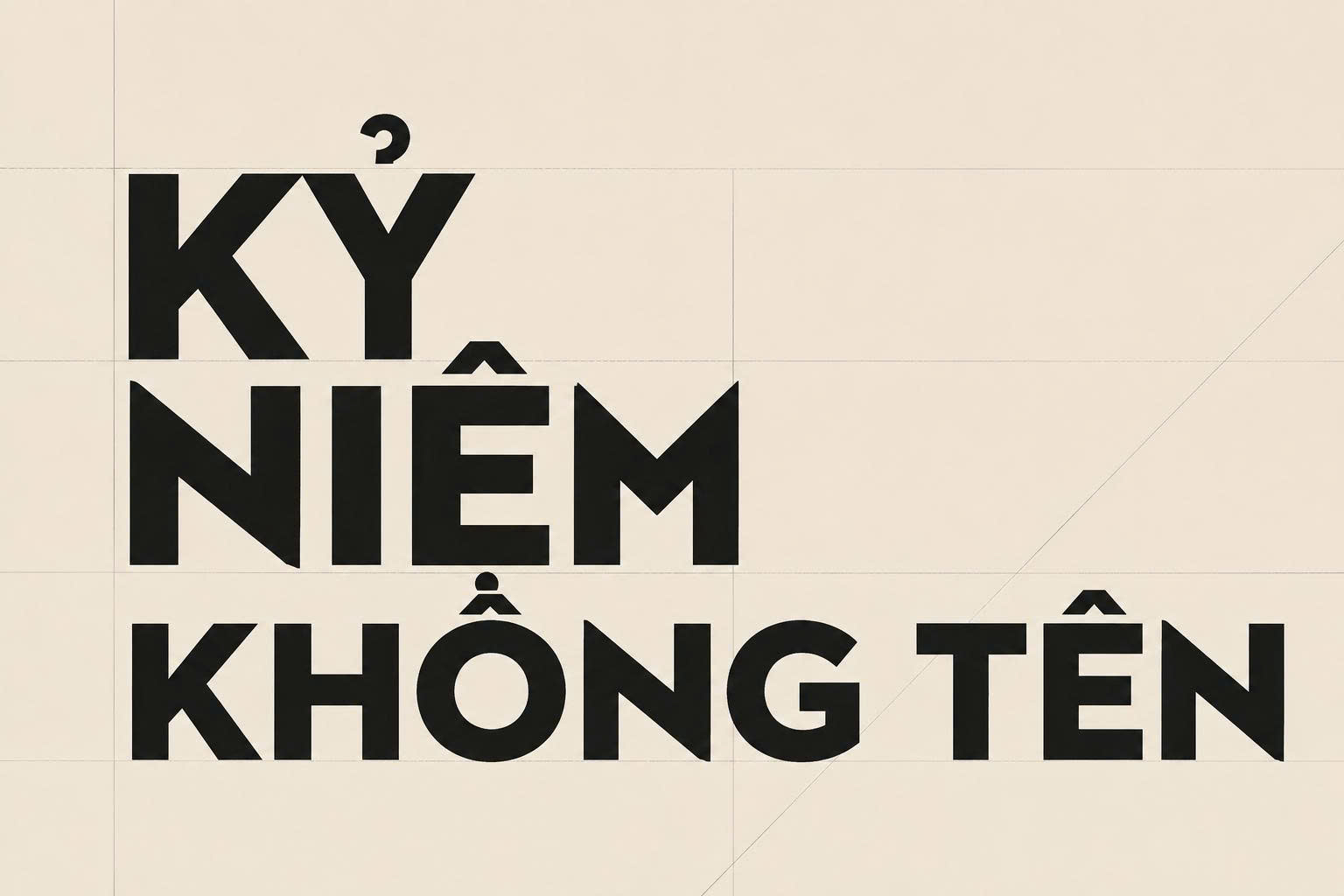
Nét vẽ tay kỹ thuật (Handwriting Drafting)
Đặc trưng lớn nhất của font chữ kiến trúc đẹp dòng viết tay là các đường nét mô phỏng áp lực của bút kim trên giấy can. Các ký tự thường có chiều cao đồng nhất, nét chữ mảnh nhưng rõ ràng, tạo cảm giác mộc mạc nhưng vô cùng chuyên nghiệp. Phong cách này gợi nhắc đến sự tận tâm của kiến trúc sư trong từng bản phác thảo sơ phác ban đầu.
Cấu trúc hình học tối giản và chuẩn xác
Ngoài dòng viết tay, font kiến trúc còn bao gồm các phông chữ không chân (Sans-serif) được xây dựng trên các khung hình học cơ bản. Những bộ font này nhấn mạnh vào sự minh bạch, hiện đại và tính logic cao. Khi được Việt hóa tại Doozypack.vn, hệ thống dấu thanh được tinh chỉnh để không làm phá vỡ sự cân bằng của các nét vẽ kỹ thuật, đảm bảo văn bản luôn thông thoáng.
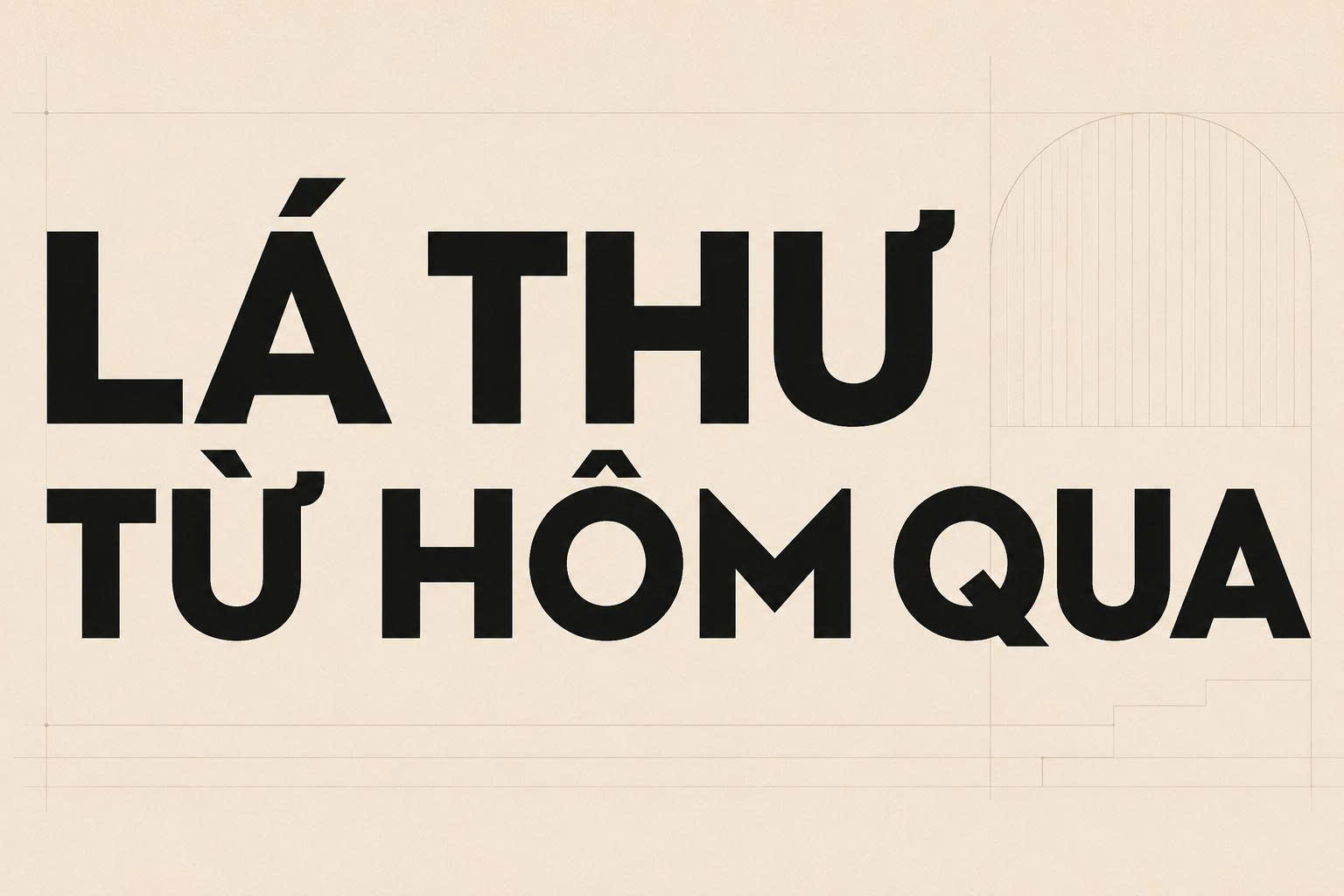
| Nhóm Font | Đặc điểm thị giác | Ứng dụng đề xuất tại Doozypack.vn |
| Font Phác thảo (Drafting) | Viết tay, mộc mạc | Dùng cho tem nhãn sản phẩm thủ công, thiệp mời studio kiến trúc. |
| Font Kỹ thuật (Technical) | Sạch sẽ, chuẩn xác | Dùng in thông số kỹ thuật, hướng dẫn lắp đặt trên vỏ hộp. |
| Font Hình học (Geometric) | Hiện đại, tối giản | Thiết kế Logo, tiêu đề trên túi giấy doanh nghiệp xây dựng. |
Tại sao designer nên tải font kiến trúc Việt hóa cho bao bì?
Trong ngành thiết kế và sản xuất bao bì tại Doozypack.vn, nhóm font chữ này mang lại những giá trị thực tế vượt trội:
- Giải quyết triệt để lỗi font: Việc sử dụng bản Việt hóa chuẩn giúp bạn gõ các từ khóa chuyên ngành như “Thiết kế bền vững”, “Vật liệu tự nhiên” một cách trọn vẹn, không bị lỗi nhảy dấu ở các chữ có dấu đặc thù như ơ, ư, đ.
- Khẳng định uy tín thương hiệu: Font chữ phong cách kiến trúc tạo cảm giác về một doanh nghiệp có chuyên môn cao, làm việc khoa học và bài bản.
- Tính ứng dụng linh hoạt: Phù hợp cho cả việc làm tiêu đề chính trên hộp quà tặng lẫn trình bày các thông số kỹ thuật chi tiết trên nhãn dán sản phẩm.
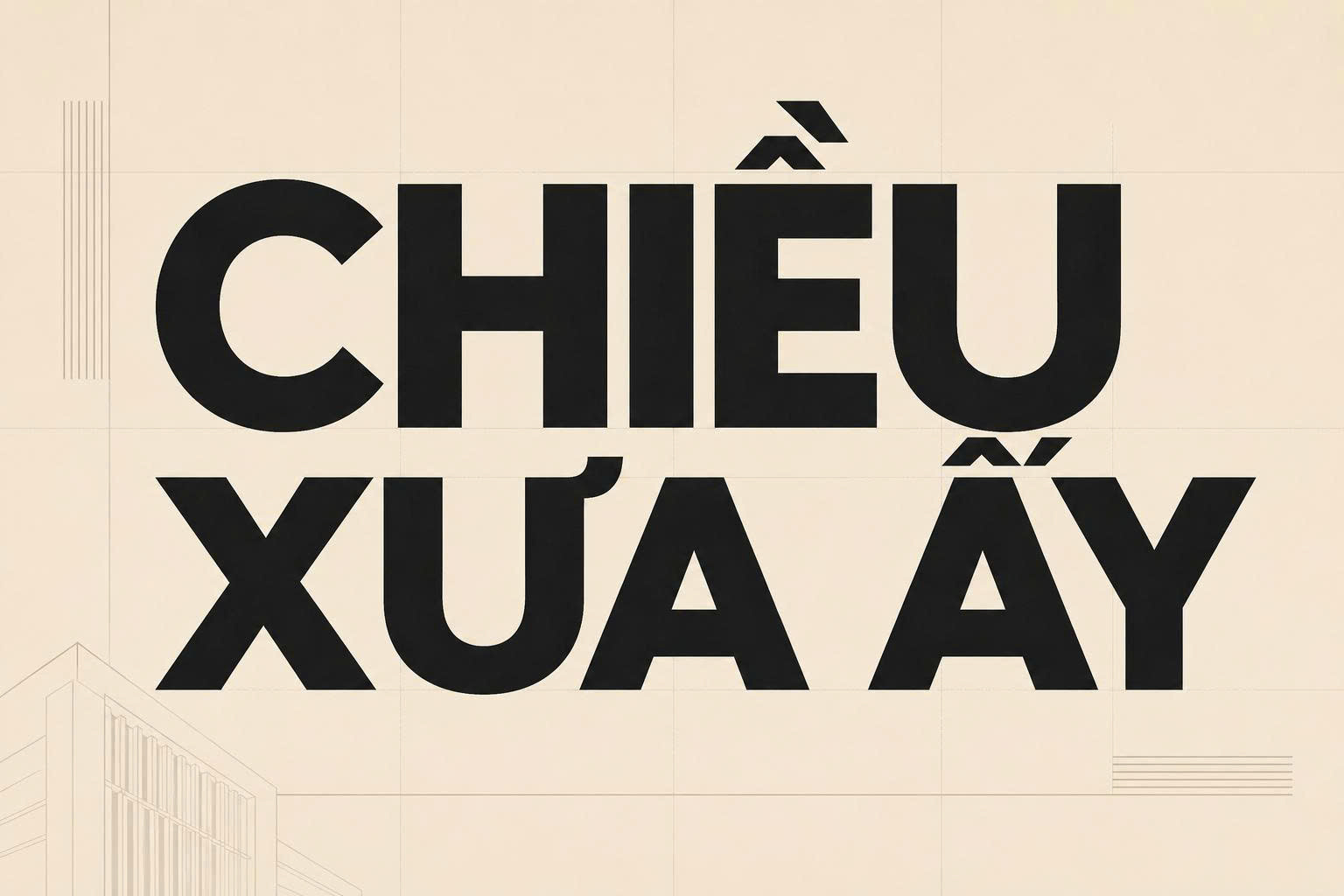
03 Ứng dụng của font kiến trúc trong sản xuất bao bì tại Doozypack.vn
Vẻ đẹp hiện đại và chuyên nghiệp của font kiến trúc mang lại hiệu quả thị giác đặc biệt trên các ấn phẩm thực tế:
- Hộp đựng phụ kiện nội thất: In tên sản phẩm và bảng thông số kỹ thuật bằng font kiến thuật tạo cảm giác đồng bộ với ngành nghề.
- Túi giấy công ty xây dựng: Tên công ty in bằng biến thể Bold hình học tạo cảm giác vững chãi và đáng tin cậy khi đối tác xách trên tay.
- Tem nhãn dán thiết bị: Cấu trúc rõ ràng của font kiến trúc giúp các bảng vẽ nhỏ hoặc sơ đồ đấu nối trên tem decal trở nên dễ tra cứu hơn.
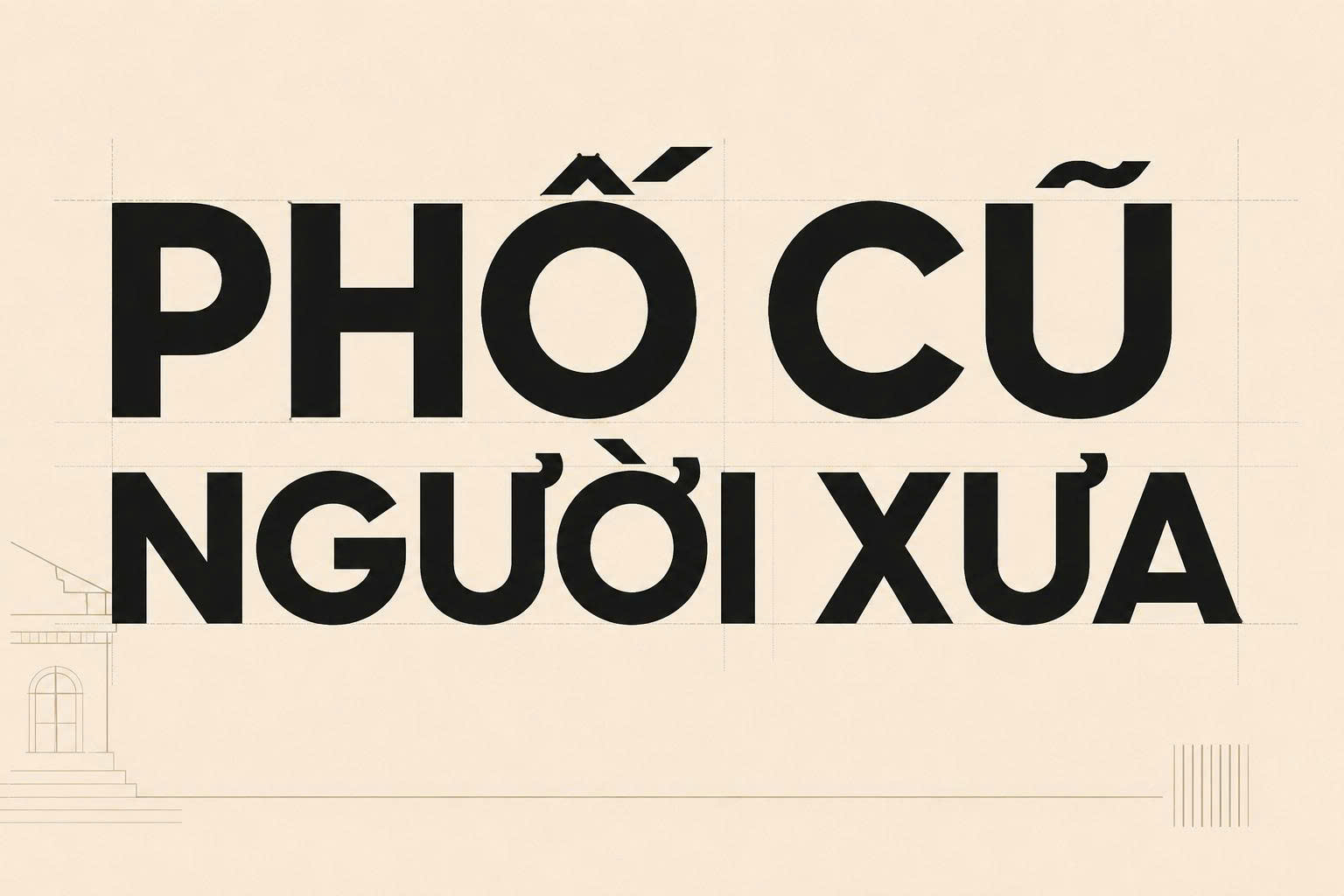
Lưu ý kỹ thuật khi in ấn font chữ nét mảnh kiến trúc
Sản xuất bao bì sử dụng phông chữ đặc thù này đòi hỏi designer cần lưu ý một số vấn đề kỹ thuật tại xưởng in chuyên nghiệp:
- Kiểm soát độ dày nét tối thiểu: Do nhiều font kiến trúc có nét mảnh như bút kim, bạn nên yêu cầu kỹ thuật viên kiểm tra độ dày nét không dưới 0.15mm để nhũ ép kim hoặc mực in bám tốt nhất.